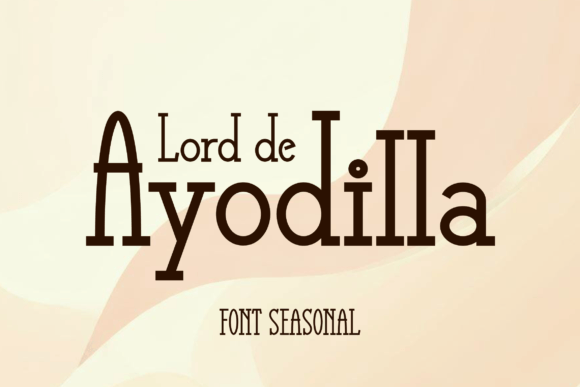
Lord De Ayodilla
適切なデザイン要素を見つけるのは難しい場合がありますが、Lord De Ayodillaは作品を即座に引き立てる優れたコレクションを提供します。
精密に作られたLord De Ayodillaは、クリーンなベクター、滑らかなタイポグラフィ、そして安心のための商用ライセンスを提供します。
POD(オンデマンド印刷)製品、結婚式の招待状、またはソーシャルメディアのグラフィックを作成している場合でも、Lord De Ayodillaは理想的です。